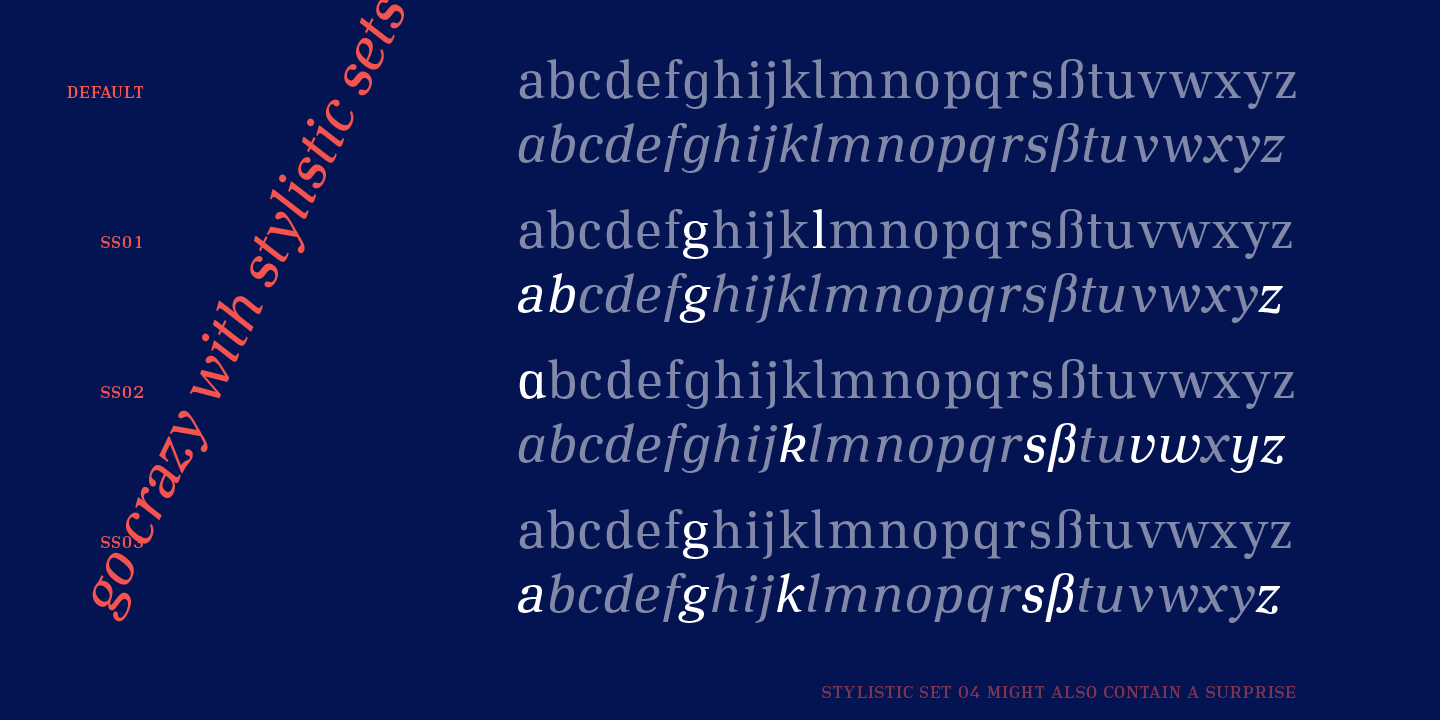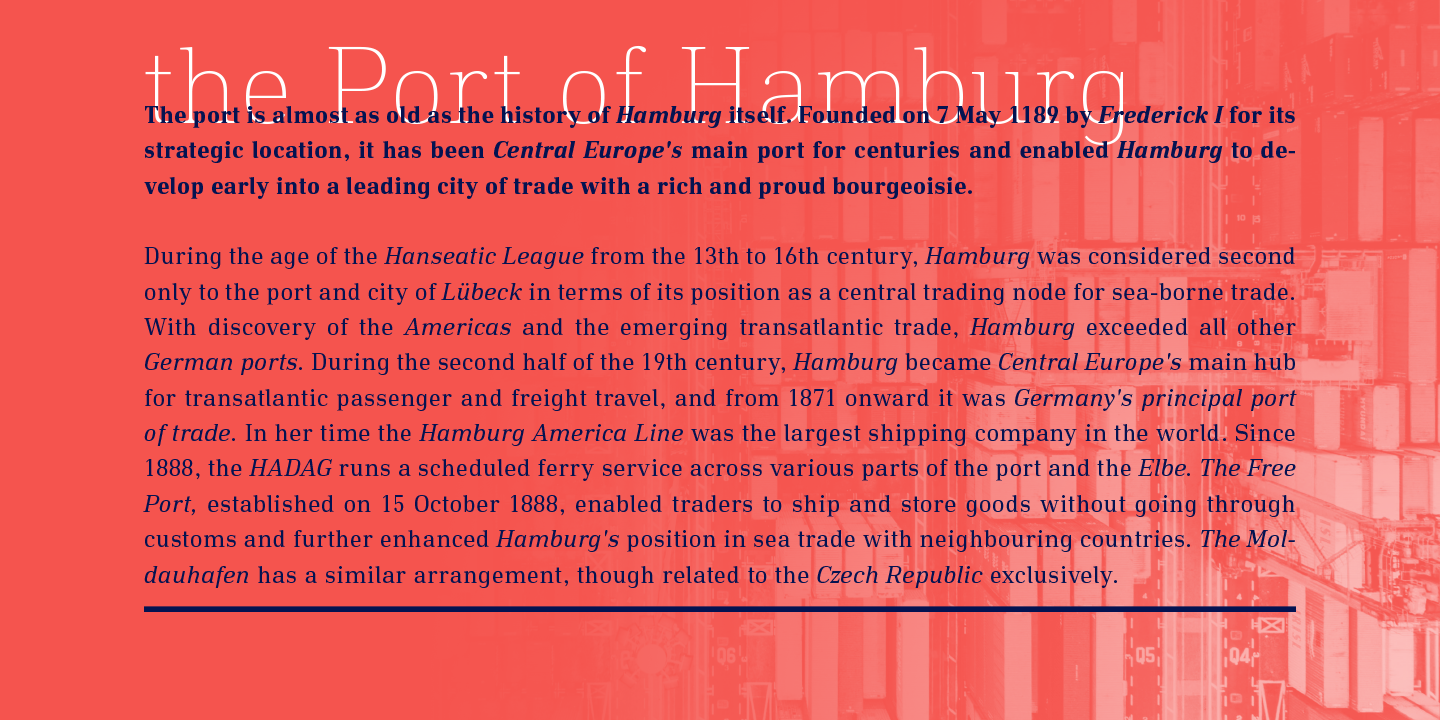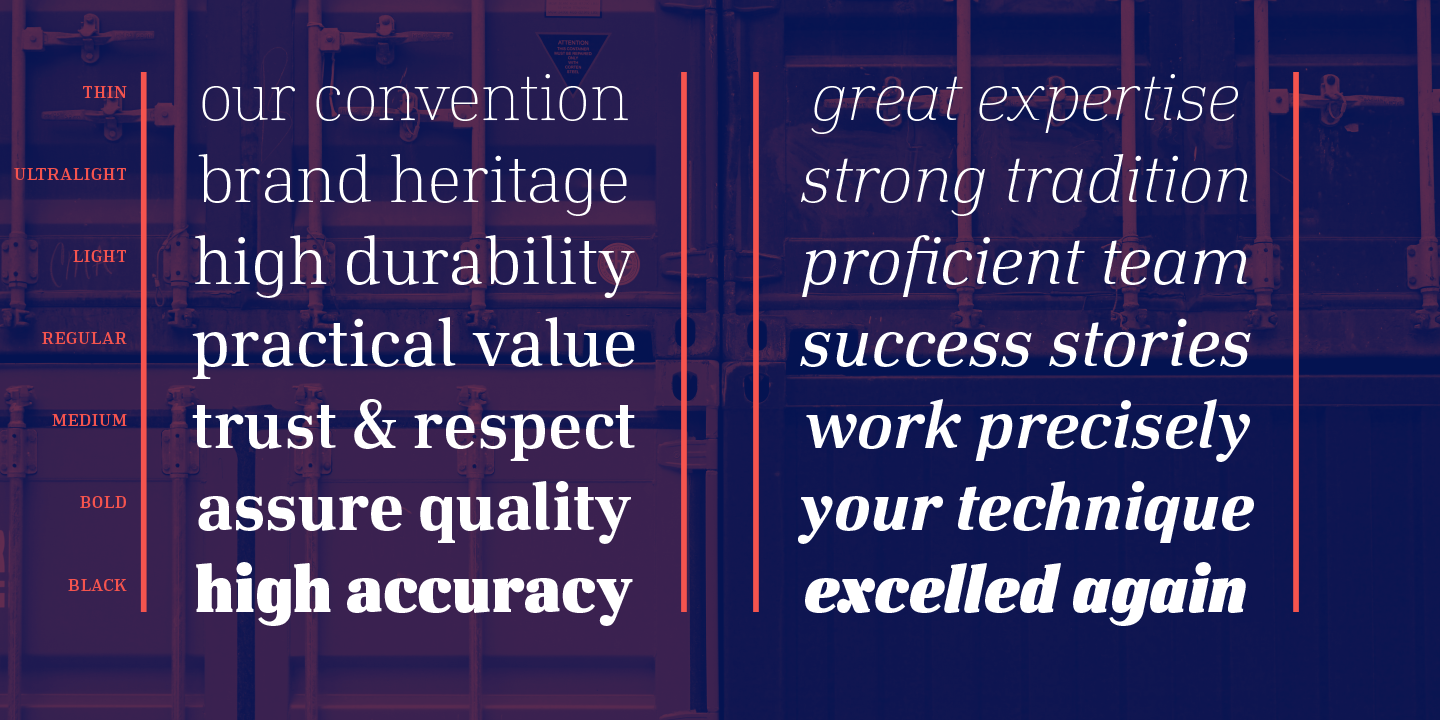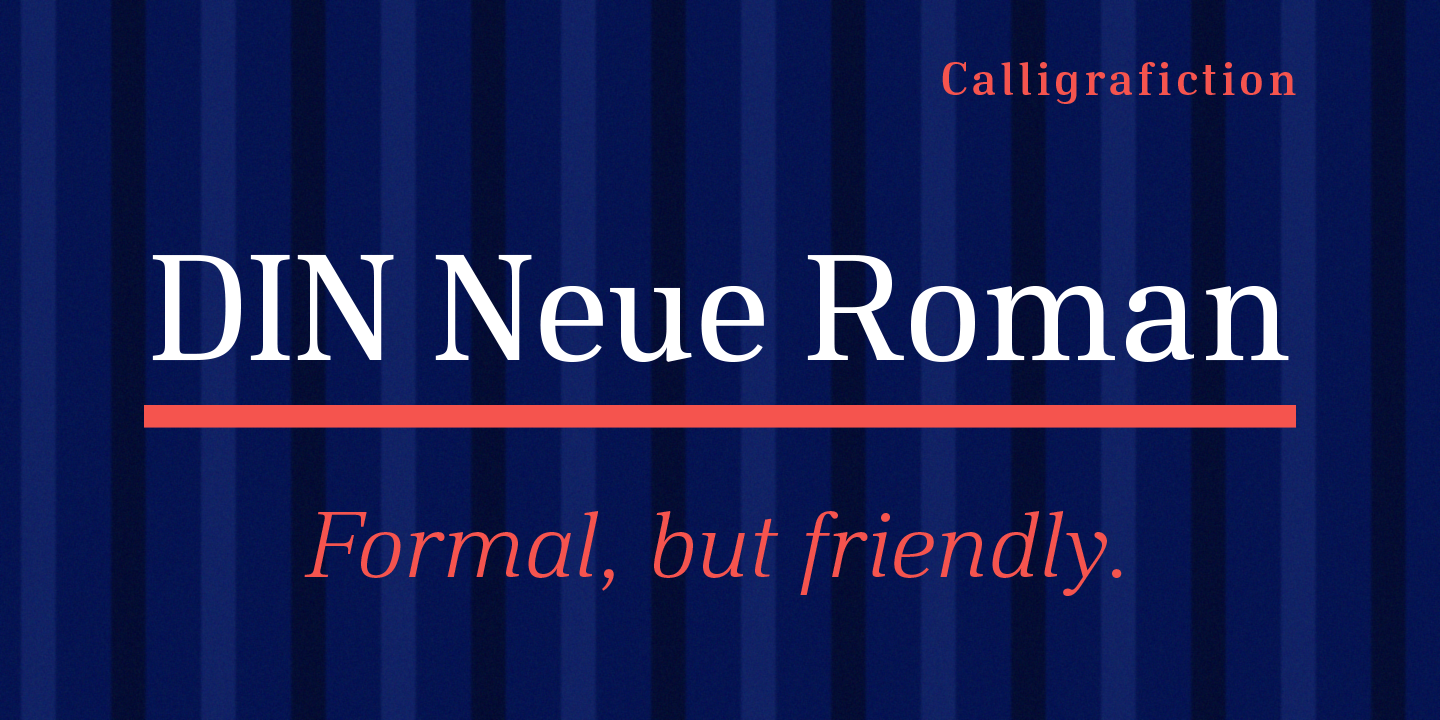
• 2015
• Serifen:
• serif
• Antiqua statisch
• Versaleszett:
• enthalten
Die DIN Neue Roman ergänzt das technische Konzept der DIN 1451 um eine neue Komponente. Als beinah elegant und freundlich wirkende Antiqua stellt sie einen tatsächlichen Ausgleich zur statisch-industriellen Anmutung ihrer Groteskvorlage dar.
Um genügend Ressourcen für vielfältige und komplexe typografische Anwendungen zu haben, bietet diese Schriftfamilie sieben Schriftschnitte mit Kursivschrift, Kapitälchen und allen Arten von Opentype-Features. Jeder Schriftstil enthält mehr als 700 Zeichen.